Cum să descărcați fonturi în Cricut pe un Mac
Publicat: 2023-02-03Dacă sunteți un utilizator Mac și doriți să utilizați fonturi în proiectele dvs. Cricut, există câteva moduri diferite în care puteți face acest lucru. În acest articol, vă vom arăta cum să descărcați fonturi în Cricut Mac SVG, astfel încât să puteți începe să le utilizați imediat în proiectele dvs. Unul dintre cele mai bune lucruri despre Cricut este că este compatibil cu o gamă largă de fonturi, ceea ce înseamnă că vă puteți personaliza cu adevărat proiectele. Dacă sunteți nou în utilizarea fonturilor cu Cricut, procesul poate părea puțin descurajantă. Dar nu vă faceți griji, vă vom prezenta tot ce trebuie să știți. Există două moduri principale de a adăuga fonturi la Cricut pe un Mac. Prima este să utilizați aplicația Cricut Design Space, care este disponibilă gratuit din App Store. Al doilea este să utilizați un manager de fonturi terță parte, cum ar fi FontBook. Dacă utilizați aplicația Cricut Design Space, procesul este destul de simplu. Doar deschideți aplicația și faceți clic pe butonul „Adăugați fonturi”. Apoi, localizați fontul pe care doriți să îl adăugați pe computer și faceți clic pe „Deschidere”. Fontul va fi adăugat în biblioteca dvs. Cricut și va fi disponibil pentru utilizare în toate proiectele dvs. Dacă utilizați un manager de fonturi terță parte, cum ar fi FontBook, procesul este puțin mai complicat. Dar nu vă faceți griji, vă vom prezenta pas cu pas. Mai întâi, deschideți FontBook și faceți clic pe butonul „Adăugați fonturi”. Fontul va fi adăugat la biblioteca dvs. FontBook. Apoi, deschideți aplicația Cricut Design Space și faceți clic pe butonul „Adăugați fonturi”. Apoi, faceți clic pe butonul „Răsfoiți” și selectați folderul „Fonturi”. În cele din urmă, faceți clic pe butonul „Adăugați” și fontul va fi adăugat în biblioteca dvs. Cricut. Cam despre asta e! Acum știți cum să descărcați fonturi în Cricut Mac SVG, astfel încât să puteți începe să le utilizați în proiectele dvs.
fonturile sunt disponibile pentru descărcare și instalare atât pe computere, cât și pe Mac, ceea ce le face simplu și convenabil de utilizat. Există numeroase moduri de a găsi fonturi gratuite online. Găsiți fonturi la modă căutând fonturi gratuite pe Pinterest. După ce ați descărcat fontul, computerul îl va putea folosi. Când fonturile sunt descărcate, acestea sunt uneori comprimate. Un fișier comprimat, spre deosebire de un folder, este o valiză plină cu haine. Când desfaci fermoarul valiza, toate hainele din interior izbucnesc, dezvăluind ce este înăuntru.
Cum instalez fonturi Svg?
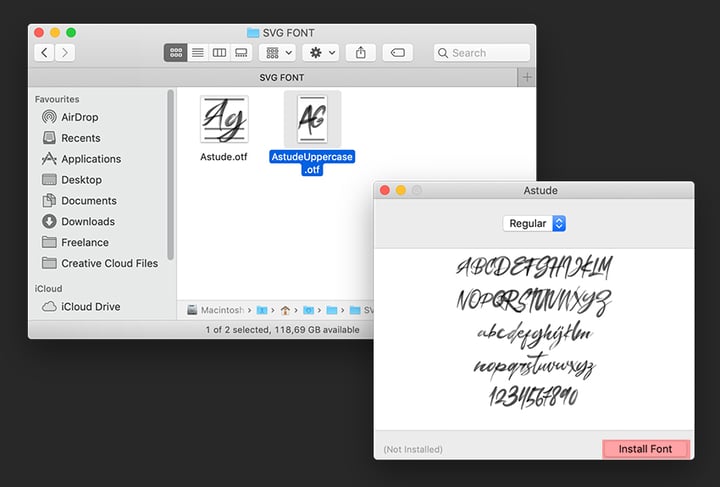
Nu există o soluție cu un singur clic pentru instalarea fonturilor SVG, dar nu este dificil de făcut. Primul pas este să găsiți și să descărcați fontul pe care doriți să îl instalați. Odată ce aveți fișierul cu font, trebuie să îl deschideți și să-l instalați ca orice alt font. Pe o mașină Windows, aceasta înseamnă de obicei să faceți clic dreapta pe fișierul fontului și să selectați „Instalare”. Pe un Mac, puteți face dublu clic pe fișierul cu font și acesta se va deschide în aplicația Font Book. De acolo, puteți face clic pe „Instalare font”.
Formatul OpenType-SVG este un tip de font în care toate sau unele dintre glife sunt afișate în format PostScript (interfață grafică scalabilă) (grafică vectorială scalabilă). Numărul de culori și combinații de gradient care pot fi afișate cu un singur glif este mai mare. Acestea ar putea include, de asemenea, funcții OpenType, care permit substituții de glif sau stiluri alternative. Dacă utilizați Adobe Illustrator, trebuie să fiți și în modul de culoare RGB. Deoarece fonturile Bitmap SVG sunt desenate manual cu texturi și transparență diferite și nu profită de formatele vectoriale, ele nu se scalează bine. Dacă există dimensiuni mari, acestea se pot pixela. Folosind panoul Glife, puteți vedea toate caracterele care sunt incluse în fontul dvs. OpenType SVG .
Puteți importa fișiere Svg în Cricut Design Space?
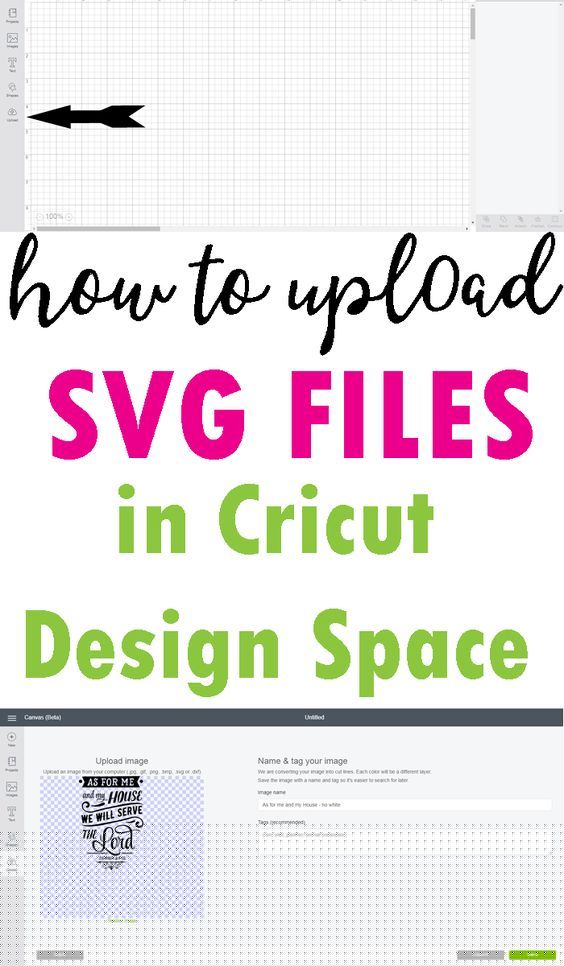
Primul pas este să deschideți software-ul Cricut Design Space pe computer (dacă utilizați software-ul pentru prima dată, poate fi necesar să vă creați un cont și să descărcați software-ul). Puteți încărca făcând clic pe pictograma „Încărcați” din colțul din stânga jos al ecranului. Când faceți clic pe pictograma Încărcare, începe procesul de încărcare a unui fișier SVG.
O grafică vectorială poate fi scalabilă folosind o tehnică cunoscută sub numele de grafică vectorială. Dimensiunea unui fișier SVG poate fi mărită sau micșorată fără a afecta calitatea acestuia. Designerii oferă frecvent fișiere SVG gratuite clienților lor. Aceste fișiere pot fi importate cu ușurință folosind programul Cricut Design Space. Drept urmare, veți putea realiza proiecte uimitoare cu freza.
Descărcați fonturi
Descărcarea fonturilor este o modalitate rapidă și ușoară de a adăuga personalitate și stil documentelor dvs. Există mii de fonturi disponibile online, iar multe dintre ele sunt gratuite. Pentru a descărca fonturi, trebuie doar să găsiți un site web cu fonturi , să răsfoiți fonturile și să faceți clic pe linkul de descărcare. Odată ce fontul este descărcat, îl puteți instala pe computer și puteți începe să îl utilizați imediat.
Fonturi Cricut
Există o varietate de fonturi diferite care pot fi folosite cu o mașină Cricut. Fonturile pot fi descărcate de pe site-ul Cricut sau de pe alte site-uri care oferă fonturi Cricut. Unele dintre cele mai populare fonturi Cricut includ următoarele: Cricut Sans: Acesta este un font simplu sans serif, care este perfect pentru orice proiect. Cricut Serif: Acesta este un font mai tradițional, care este perfect pentru proiectele care necesită un aspect mai formal. Cricut Script: Acesta este un font perfect pentru proiectele care necesită un aspect mai jucăuș sau mai capricios. Cricut Decorative: Acest font este perfect pentru proiectele care necesită un aspect mai ornamentat sau decorativ.
O bibliotecă de fonturi poate servi drept bază pentru orice proiect de design, indiferent dacă sunteți designer grafic sau artizan. Nu numai că vor funcționa cu programele tale preferate, dar vor funcționa și cu mașini de tăiat. Acest șablon poate fi folosit pentru a crea anunțuri banner pe rețelele sociale, precum și pentru a crea foi de lucru, jurnale, bloguri și alt conținut. Această licență vine cu drepturi de utilizare atât personale, cât și comerciale. Utilizați cele mai bune fonturi Cricut în lucrările dvs., cum ar fi grafice cu citate, tricouri, jurnale și multe altele. Cu o gamă largă de stiluri, această colecție fantastică include scripturi elegante și stiluri funky sans serif. Când vă spălați proiectele de artă sau meșteșuguri, puteți simți o legătură specială cu ele.
În 1001 Free Fonts (se deschide într-o filă nouă), nu există un program 1001 Free Fonts . Există numeroase fonturi gratuite disponibile în categoriile 64 și puteți, de asemenea, să răsfoiți după designer. Biblioteca de fonturi Neogrey nu este o bibliotecă de fonturi în sensul că nu este o bibliotecă de fonturi ca atare, ci mai degrabă un portofoliu al unui designer, Ivan Filipov. Este ușor să găsești gratuități unice (în noua filă) la Fontfabric. Liga tipurilor mobile va oferi o revoluție tipografică în viitor. Riley Cran și Tyler Galpin, care au fondat Lost Type, vă oferă posibilitatea de a plăti pentru orice font doriți. Rosie Hilder este redactor adjunct la Creative Bloq. Și-a început cariera în jurnalism în Argentina, unde abilitățile ei de blogging au condus la numirea ei ca redactor adjunct al Time Out Buenos Aires. Îi place designul grafic, brandingul și ilustrația, precum și tehnologia și sexismul.